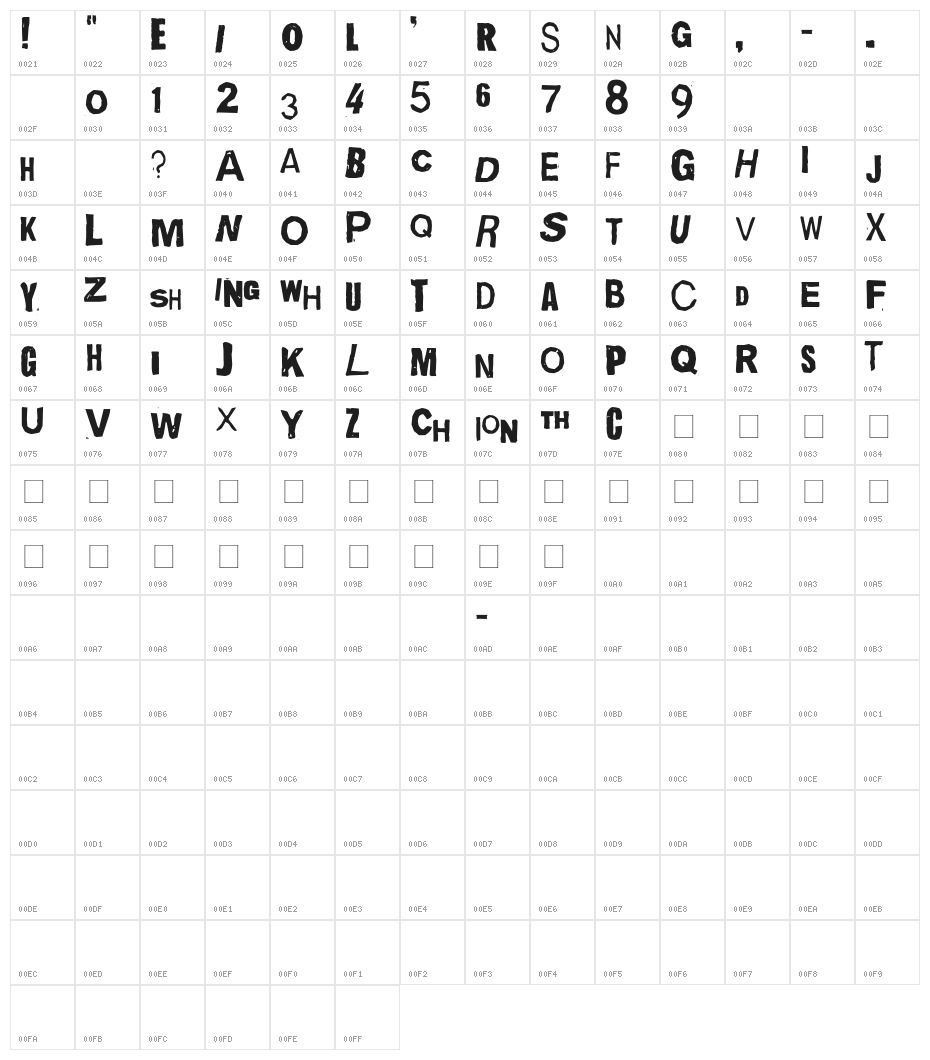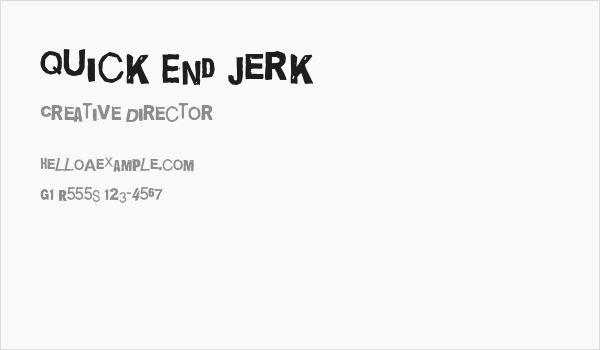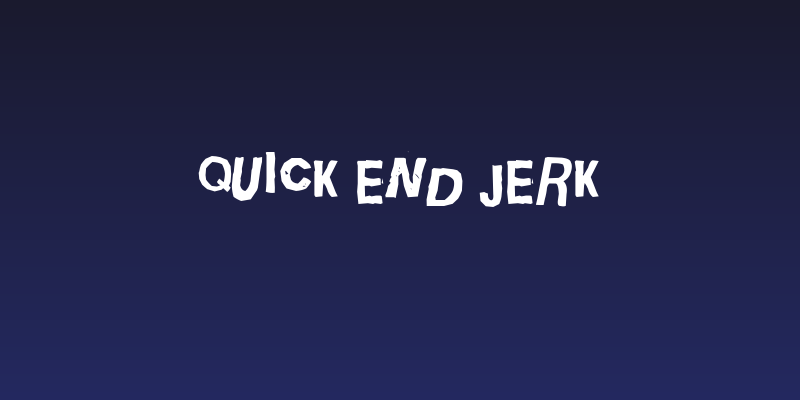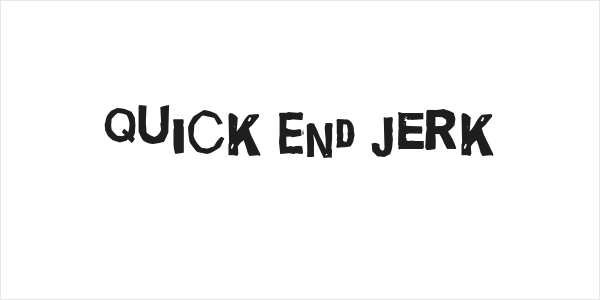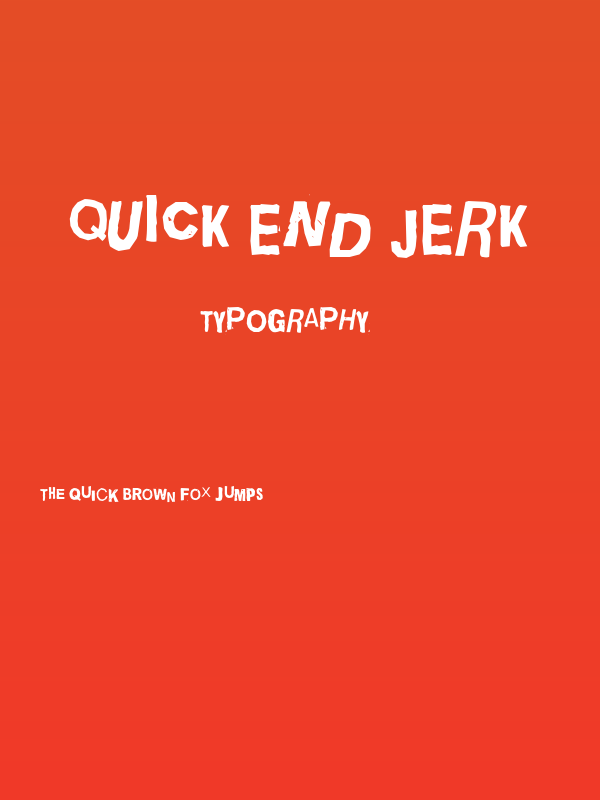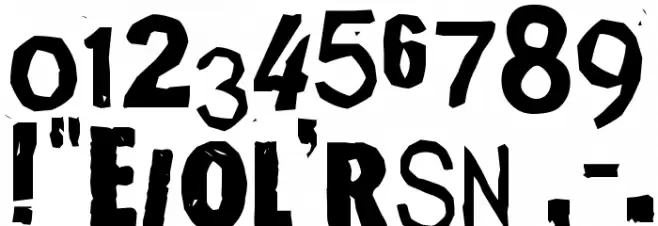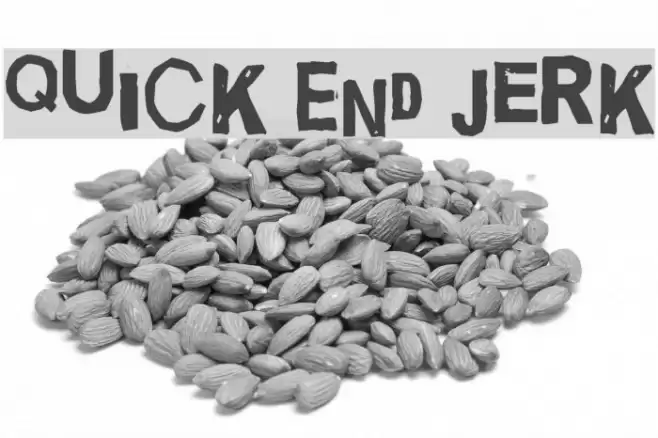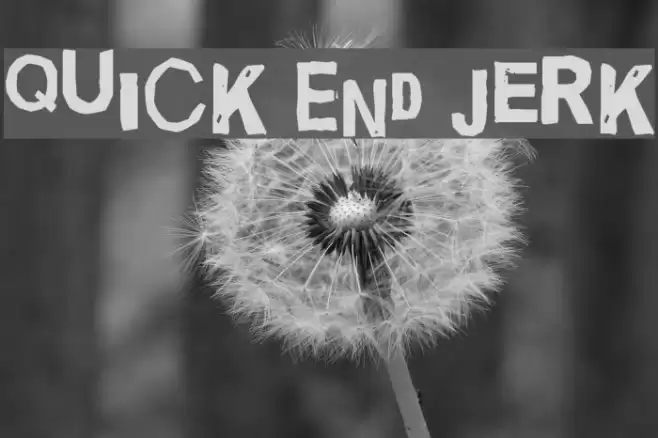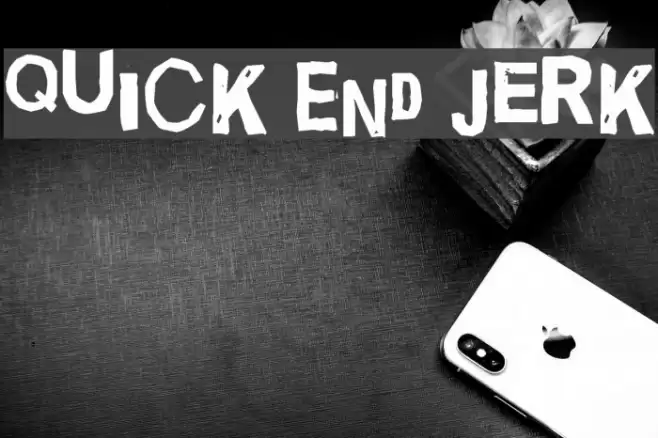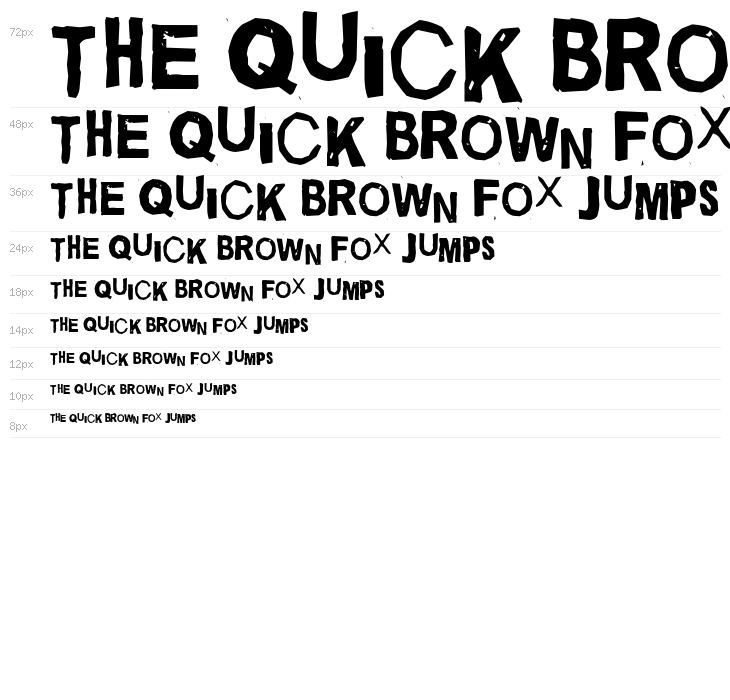
Quick End Jerk Font
✎ Distorted Eroded
| Proyectos propuestos | Ideal for posters, album covers, street art-inspired designs, and creative branding. |